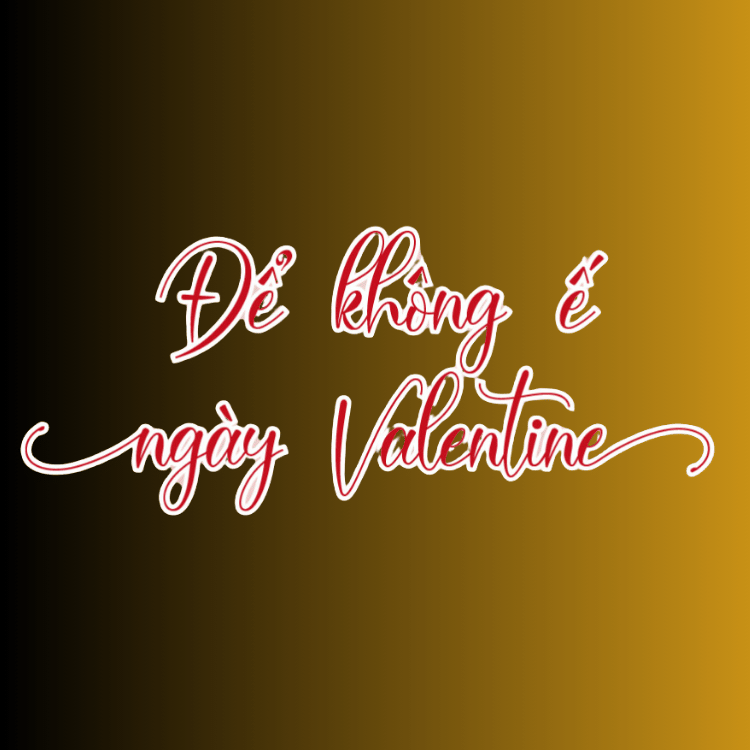
Giới thiệu về Font Việt hóa VIP Bailey , Font cho valentine
Ngày lễ tình nhân đang đến gần, nhu cầu tìm kiếm các bộ Font Miễn Phí để thiết kế thiệp mừng và quà tặng ngày càng tăng cao. Trong số đó, Font Việt hóa VIP Bailey , Font cho valentine nổi lên như một lựa chọn hàng đầu nhờ phong cách thanh lịch và bay bổng. Đây là bộ phông chữ được tinh chỉnh kỹ lưỡng để hỗ trợ đầy đủ tiếng Việt, giúp các bạn học sinh và người yêu thiết kế dễ dàng tạo nên những tác phẩm nghệ thuật đậm chất cá nhân. Với đường nét mềm mại, bộ font này không chỉ mang lại vẻ đẹp thẩm mỹ mà còn truyền tải thông điệp yêu thương một cách trọn vẹn nhất.
Tại sao nên chọn Font Việt hóa VIP Bailey , Font cho valentine?
Bộ Font Việt hóa VIP Bailey , Font cho valentine sở hữu cấu trúc ký tự hài hòa, rất phù hợp cho các tiêu đề thiệp cưới, banner sự kiện hoặc các bài đăng trên mạng xã hội vào dịp 14/2. Điểm đặc biệt của phông chữ này là các nét nối (ligatures) đầy tinh tế, tạo cảm giác như chữ viết tay tự nhiên. Việc sử dụng phông chữ phù hợp sẽ giúp sản phẩm thiết kế của bạn trở nên chuyên nghiệp và thu hút hơn trong mắt người nhận.
Cách ứng dụng Font Việt hóa VIP Bailey trong thiết kế học đường
Đối với các bạn học sinh, việc sử dụng Font Việt hóa VIP Bailey , Font cho valentine trong các bài thuyết trình hay báo tường sẽ tạo điểm nhấn khác biệt. Bạn có thể kết hợp phông chữ này với các tông màu hồng, đỏ hoặc pastel để làm nổi bật chủ đề tình bạn và tình yêu lứa đôi.